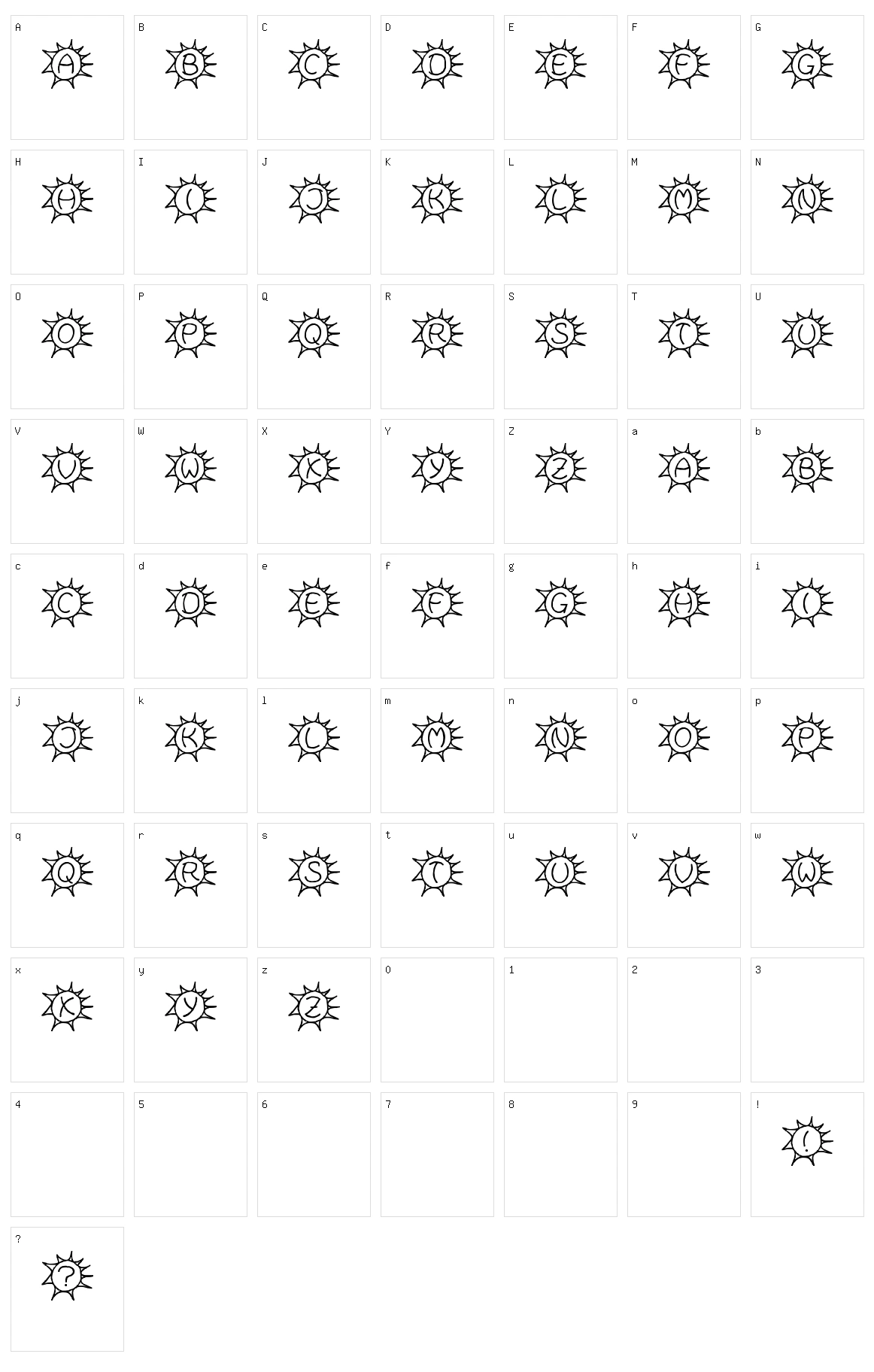
Juhu, es hat geklappt, nachdem ich Sonnenschein gemacht hatte, schien bei uns wirklich
wieder die Sonne. Vor Freude habe ich gleich eine weitere Sonnenschrift gemacht. Ich wünsche
euch viele sonnige Tage.